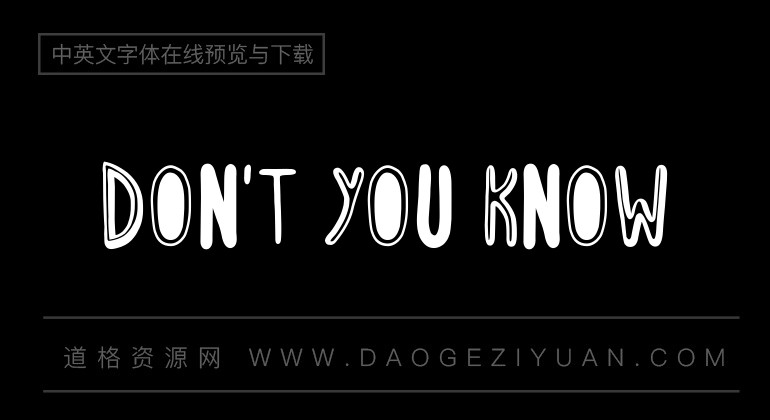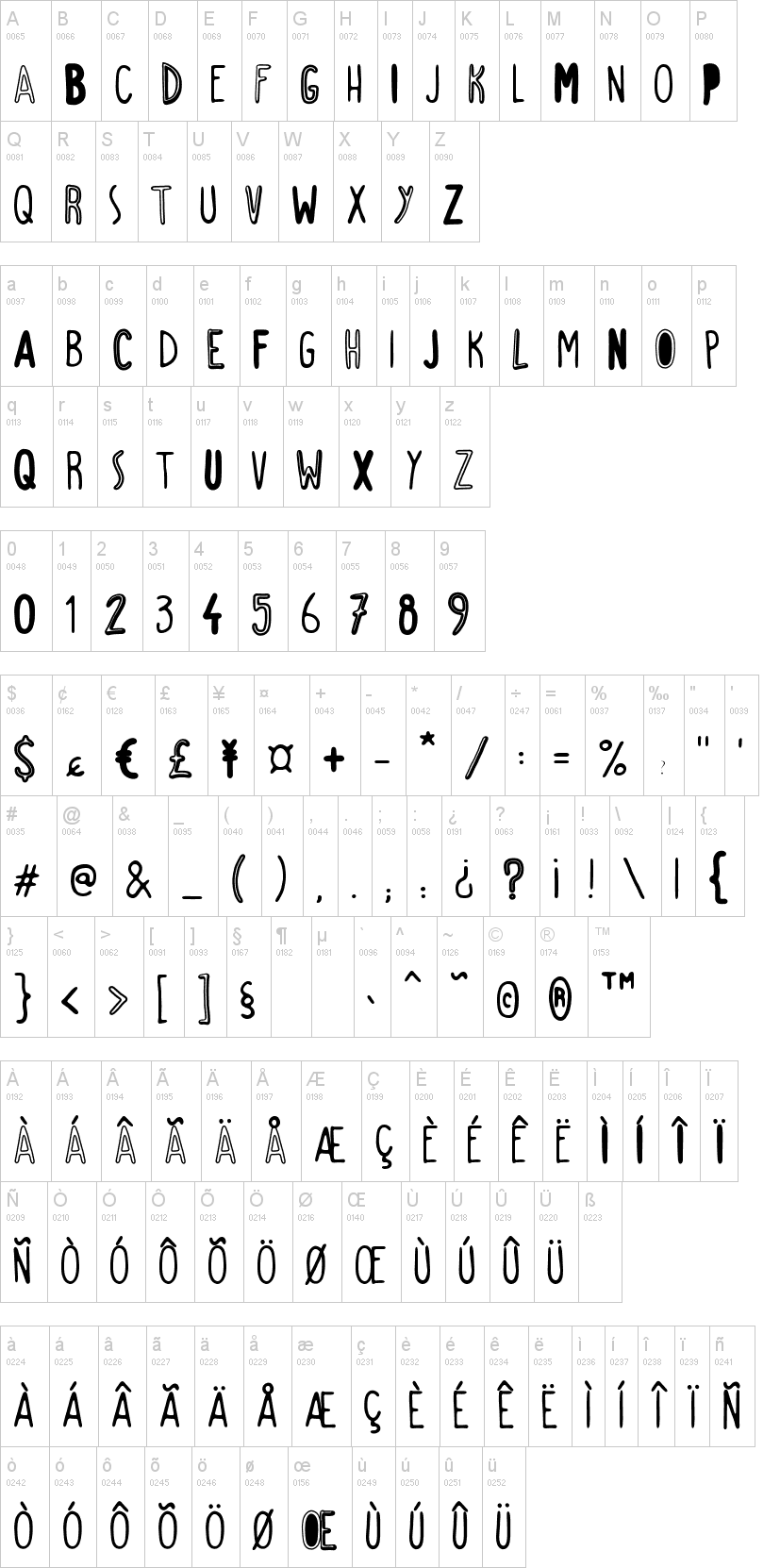
Don't You Know 字体是一种现代手写风格的字体。它的设计师是来自荷兰的敏感性创意工作室Måns Grebäck。这种字体具有流畅的笔画和有机的形状,看起来非常自然和舒适。Don't You Know 字体的每个字母都带有一个独特的风格,使得它在设计中非常适用于横幅、海报、广告和其他需要突出文本的设计作品。内容介绍
Don't You Know是一款非常不错的手写艺术字体,具有很好的视觉感,适合于文化类的宣传设计、商业类品牌的广告和产品包装设计以及个性化文字排版等较多场景。